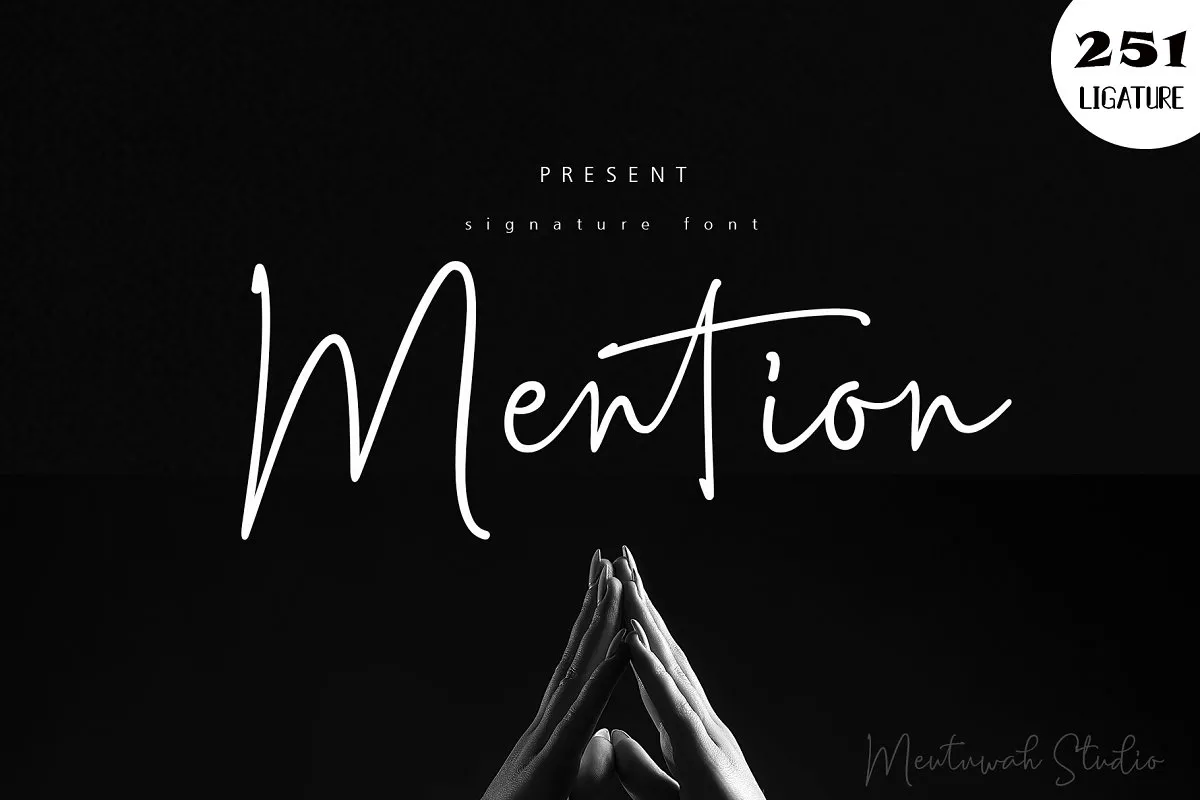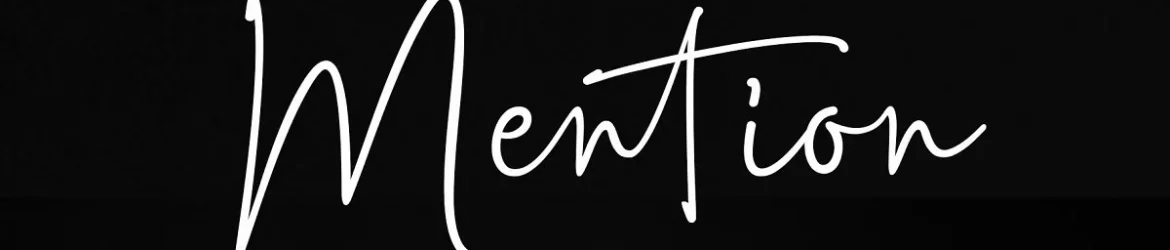
Mention Signature Font – Download Grátis
Introduzimos a fonte de script “Mention” – uma assinatura moderna escrita à mão com um fluxo natural. Este script foi desenvolvido e compartilhado por Meutuwah, apresentando o seu próprio toque elegante ao entrelaçar influências do xamanismo clássico com a modernidade. O design “Mention” é outro belo script de assinatura que une a sofisticação da escrita filosófica tradicional com uma abordagem contemporânea, utilizando elementos dos antigos platinados e tipografia contemporâneas em movimento. As alternativas e ligaturas incluídas adicionarão ainda mais personalidade ao seu trabalho final. Se você está procurando por um script de assinatura que combine a elegância de uma escrita filosófica clássica com o desenho moderno e vibrante, “Mention” pode ser a fonte perfeita para você.